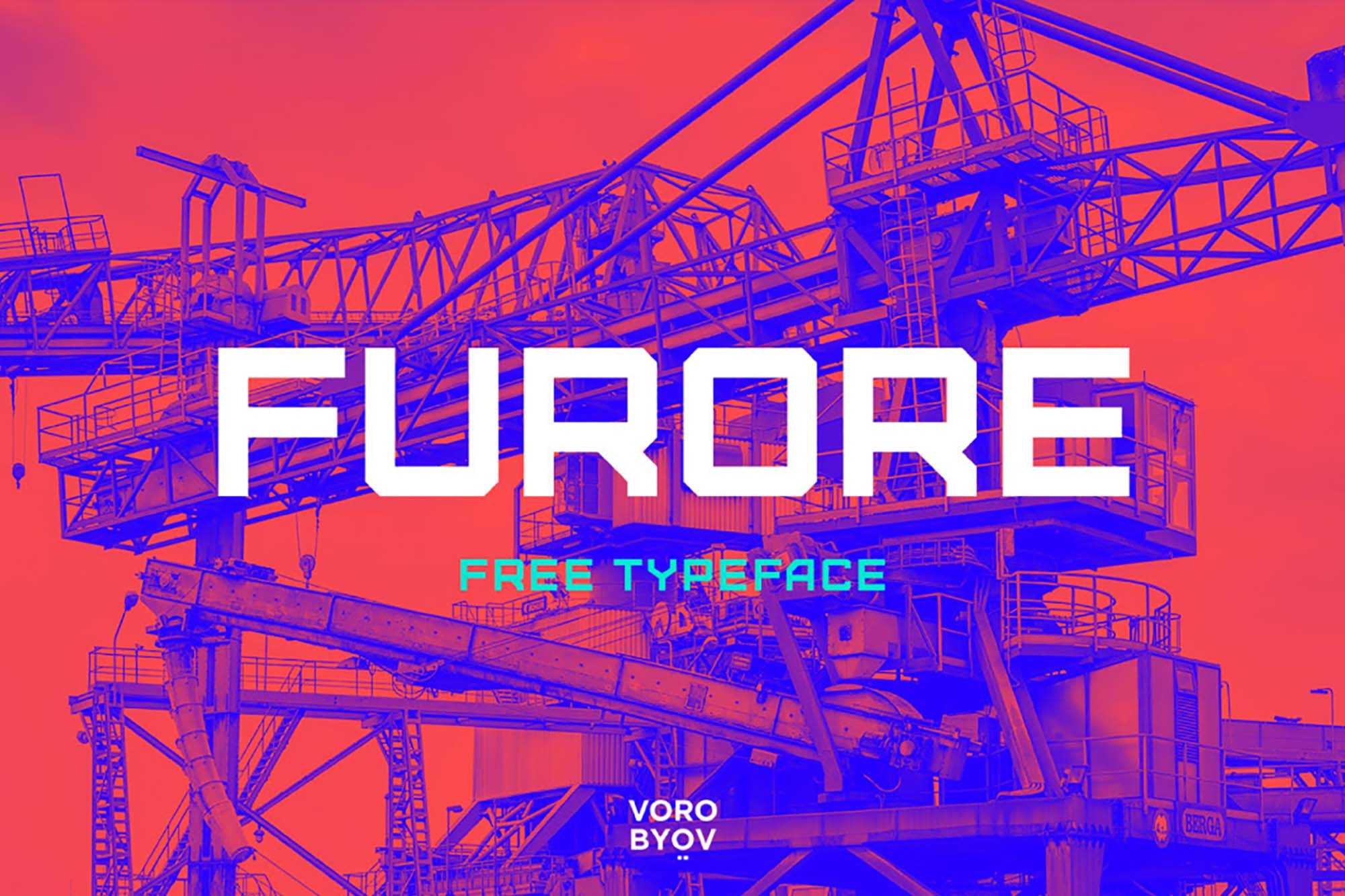
Furore Industrial Sans Serif Font – Download Grátis
A fonte “Furore Industrial Sans Serif” é uma escolha inteligente para quem busca um estilo robusto e moderno. Seu design industrial transmite confiança e força, perfeito para aplicações que exigem leitura clara e impacto visual. Embora muitos fontes gratuitas ofereçam uma variedade de estilos, poucos conseguem capturar a elegância e sutileza de um tipo cuidadosamente concebido por um designer profissional. A Furore Industrial é uma ótima opção para quem busca um recurso gráfico que transmita uma imagem sólida e confiável, sem comprometer a legibilidade. Sem dúvida, um investimento valioso para projetos que buscam um estilo moderno e forte.